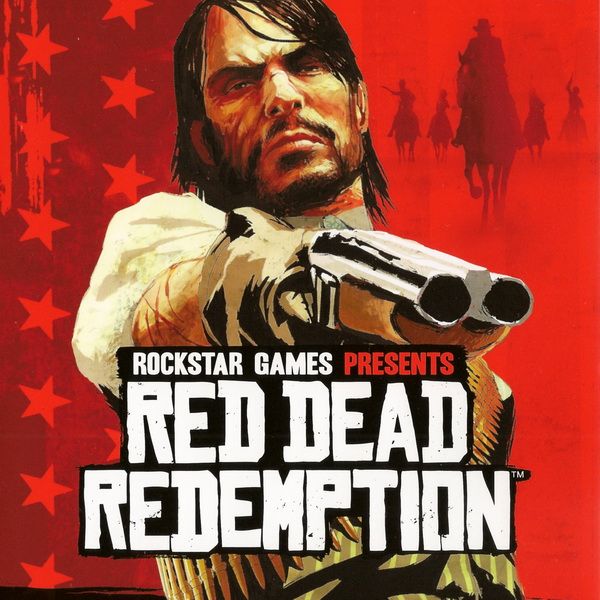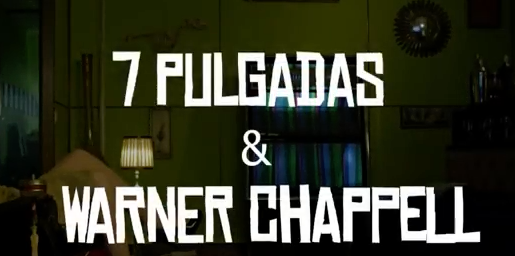
Hola! Se me ocurren 2 parecidas: Spongeboy Me Bob y Fifties Movies.
Siiiii!!! Gracias Samuel, esa fuente me vale!!! Muchas gracias, ah y por cierto es verdad que es un juegazo, lo tengo y estoy to enganchá.... jejejeej ;)
Chinese rocks, es una fuente comercial pero este peso lo tienes for free.
Por cierto, es la misma de Red Dead Redemption. Juegazo.
Demasiadas diferencias en las letras para ser una tipografía, ¿no? Examina las dos P de CHAPPEL.